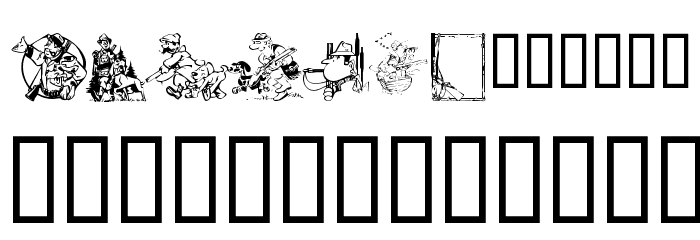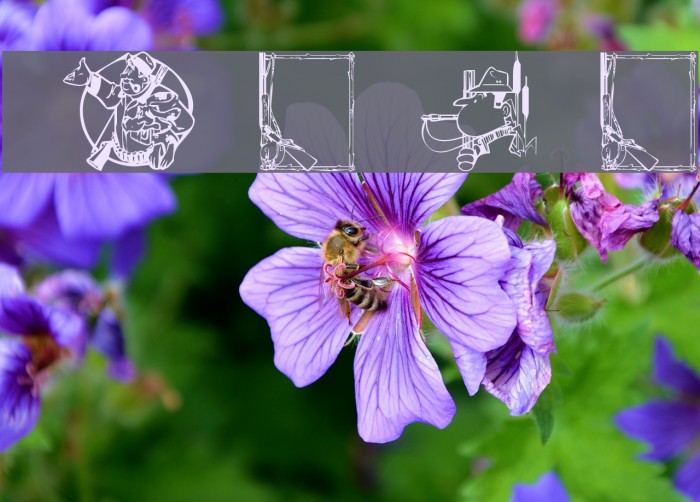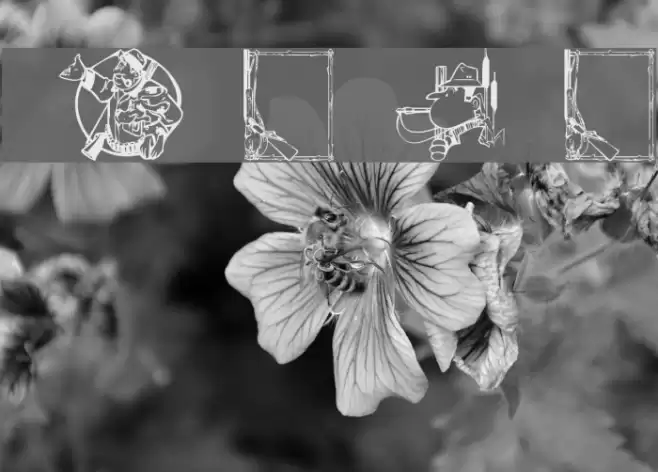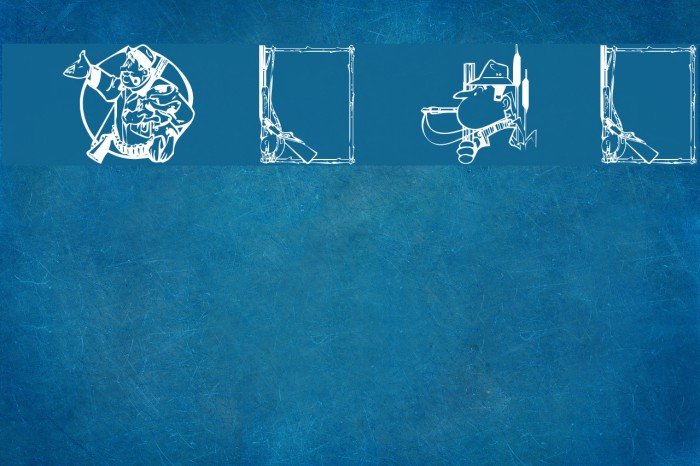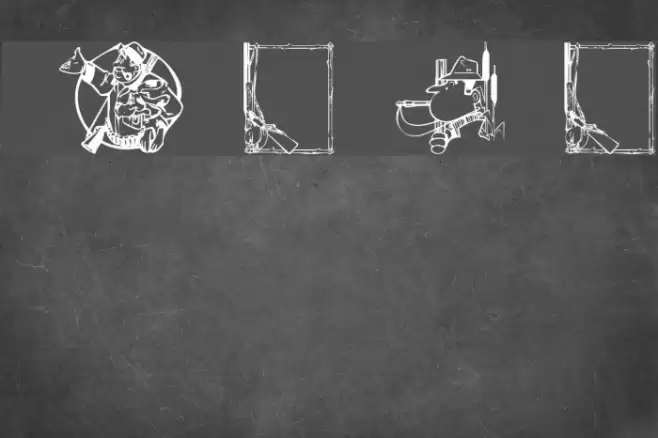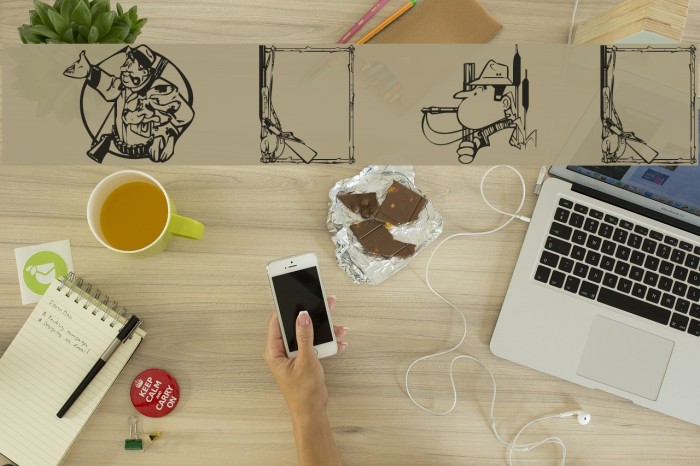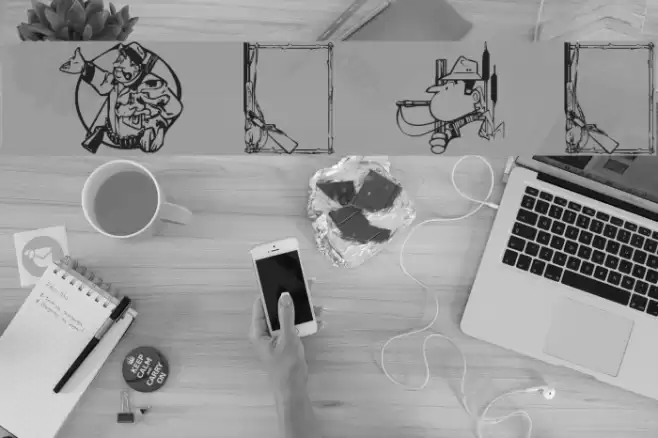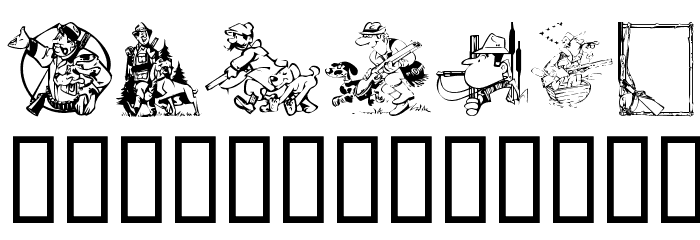
KR A Hunting We Go Font
| Cas d'utilisation | Decorative elements, Themed projects |
| Projets proposés | Ideal for themed invitations, scrapbooking, or decorative elements in hunting-related publications. |